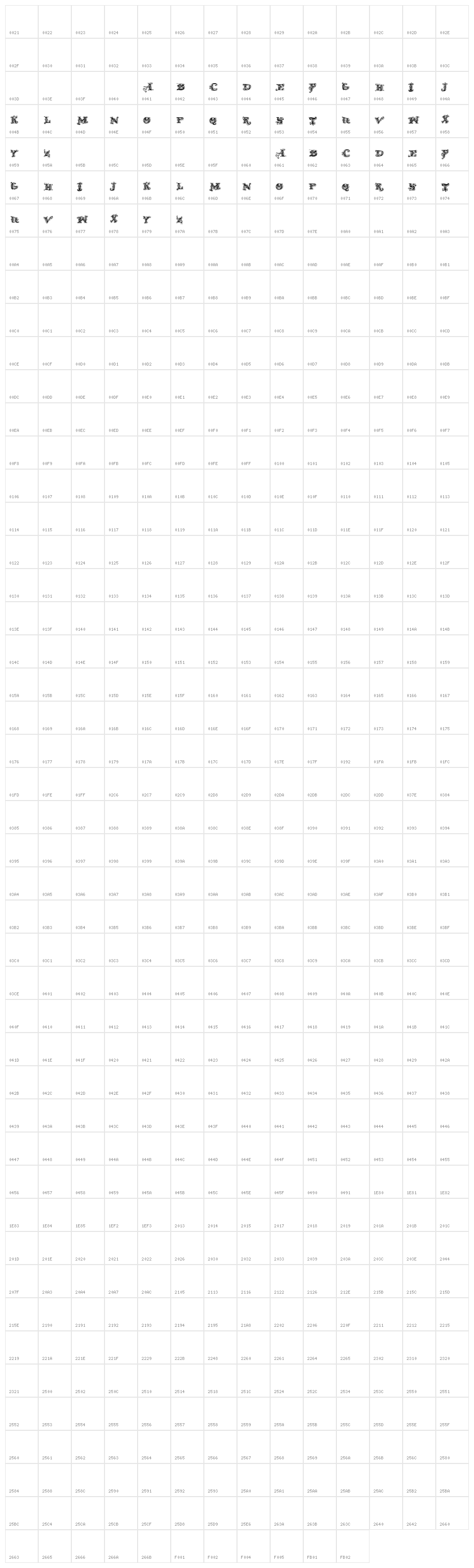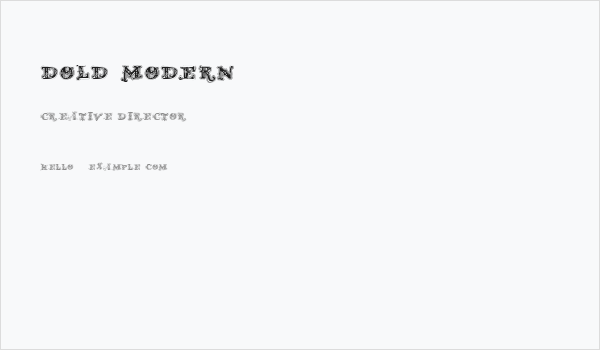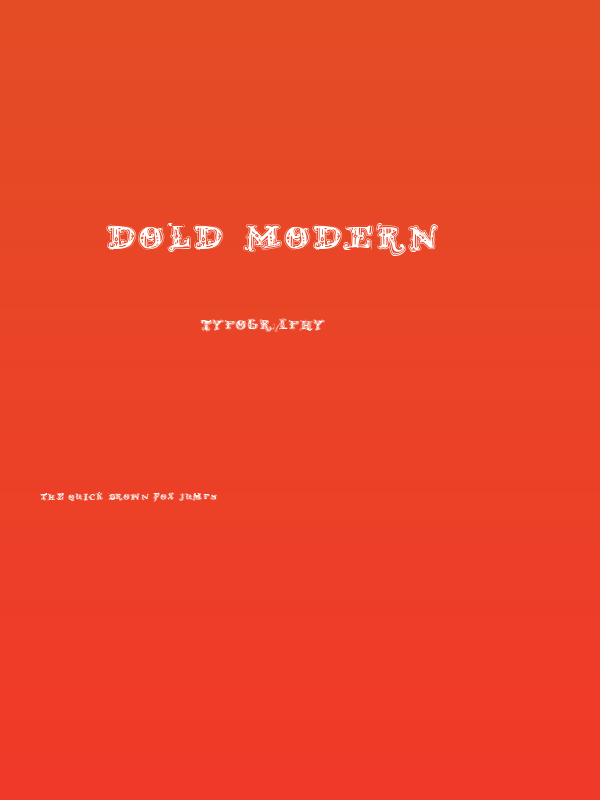
D_OLD MODERN 2 Font
✎ Crazy
| Progetti proposti | Ideal for vintage posters, wedding invitations, book covers, and branding that requires a classic touch. |